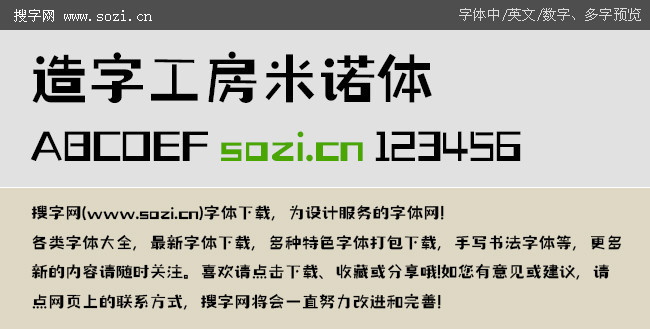
造字工房米諾體
搜字網(wǎng)給大家提供一款造字工房米諾體中文字體下載,造字工房米諾體字體中宮寬闊、字面飽滿,筆畫粗細穿插有序,點畫巧用圓點使得此套字體寬博又不失靈動,神形兼?zhèn),風格隨性自然,活潑俏皮。適用于大標題、包裝設(shè)計、海報設(shè)計等應(yīng)用。(本字體為個人非商用版,如需要商用請聯(lián)系官方購買版權(quán))